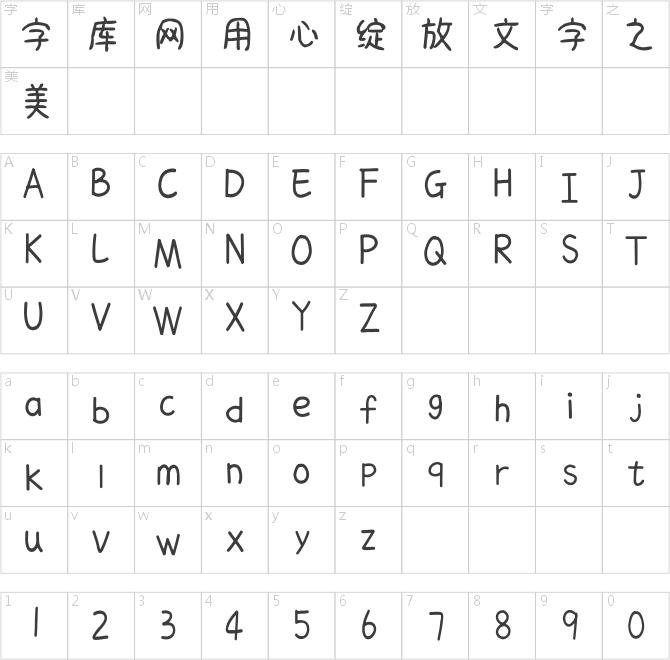
今日份快樂(lè)源泉
今日份快樂(lè)源泉字體下載
今日份快樂(lè)源泉字體字庫(kù)是一款讓人賞心悅目、百看不厭的中文字體,適合各類廣告和產(chǎn)品包裝設(shè)計(jì)應(yīng)用,字體大小2.66MB,格式為ttf字體,上傳用戶是文道字庫(kù),作者/版權(quán)方為文道字庫(kù)